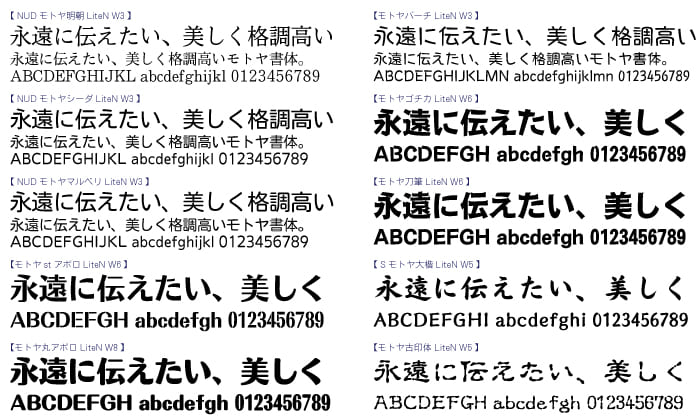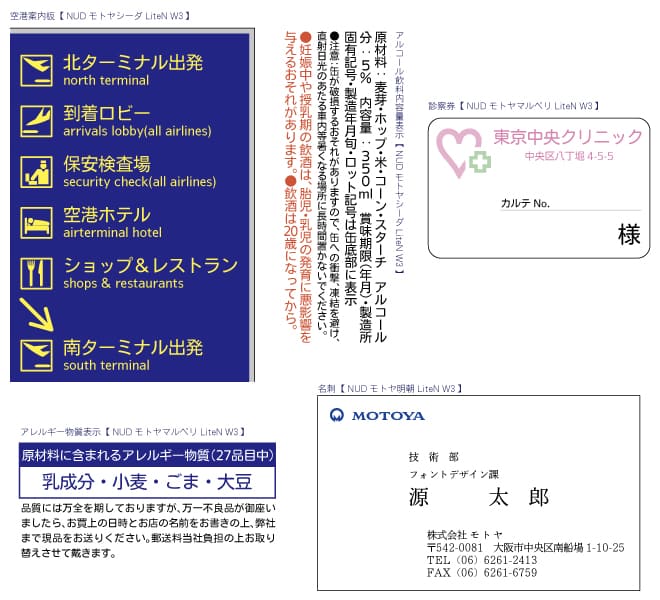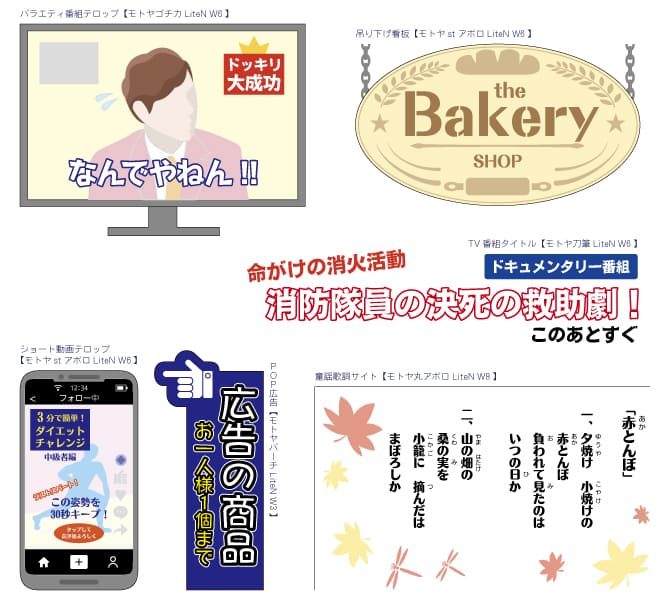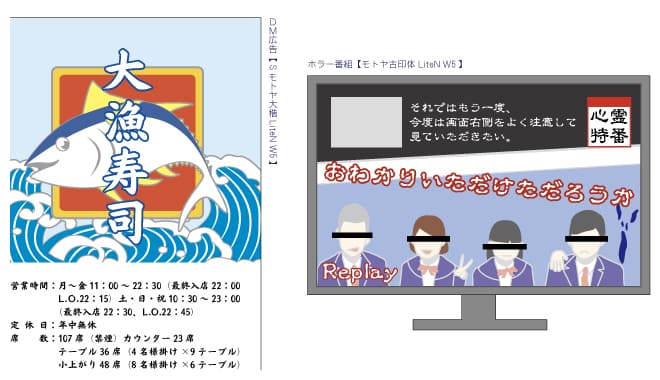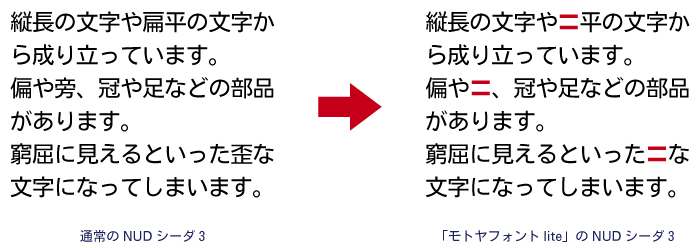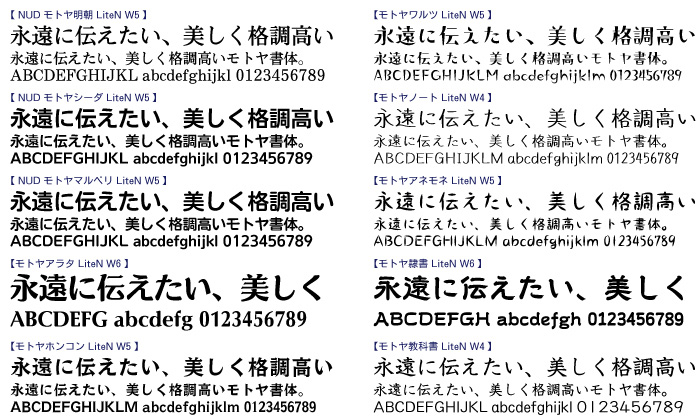
モトヤフォントlite
文字種限定 低価格商品「モトヤフォントlite」について
「モトヤフォントlite」は、文字種を改定常用漢字(2,136 字)や人名用漢字(863 字)などに限定した、1 書体5,500 円(税込)の低価格商品です。 また、「モトヤフォントlite」は、標準的な文章表現に使用できる必要最低限の文字種が収録されていますので、YouTube やTikTok 配信者をはじめ、様々なシーンでクリエイティブな活動をされている方におすすめの商品となります。
文字セット 改定常用漢字(2,136字)、人名用漢字(863字)、JIS X 0208全角非漢字
JIS X 0201プロポーショナル英数字・半角カタカナ 合計3,681文字
※「令和」を含む和暦の合字は収録していません
※異体字切り換え技術のIVS(異体字シーケンス)に対応しています
バラエティー豊かな20 書体をラインナップ!
「モトヤフォントlite」では、クリエイティブなシーンでご使用いただけるUD 書体やデザイン書体、筆文字書体などのバラエティー豊かな20 書体をラインナップしています。
モトヤフォント lite 書体例
【UD 書体】
モトヤUD(ユニバーサルデザイン)書体は、大文字化対応や太さの調整、シンプルな文字構成で通常のフォントより可読性・視認性・判読性に優れており、様々な分野での活用が可能です。大手コンビニ弁当の商品情報のラベルにも採用されている、読みやすく見やすいモトヤのUD 書体は各種施設の職員の方が作成される案内チラシやポスターなどにも最適です。
モトヤフォント lite UD書体 例
【デザイン書体】
モトヤのデザイン書体には、バリエーション豊かな書体がラインナップされており、印刷はもちろん、Web や映像・動画(画像化して使用)にも使える分かりやすい使用許諾内容なので、YouTubeやTikTok 配信者をはじめ、様々なシーンでクリエイティブな活動をされている方におすすめです。
モトヤフォント lite デザイン書体 例
【筆文字書体】
モトヤの筆文字書体は、プロの書家の監修により制作されており、伸びやかな筆使いや墨の香りがします。
テレビテロップや新聞紙面などにも採用実績があり、映像・動画(画像化して使用)やポスター・チラシのさらなるクオリティアップに役立ちます。
モトヤフォント lite 筆文字書体 例
「モトヤフォントlite」は、文字種を改定常用漢字や人名用漢字などに限定したモトヤ独自の文字セット(合計3,681文字)を採用しています。 そのため、収録していない文字を入力すると「〓」が表示され、文字化けによる印刷事故に繋がりますのでご注意ください。